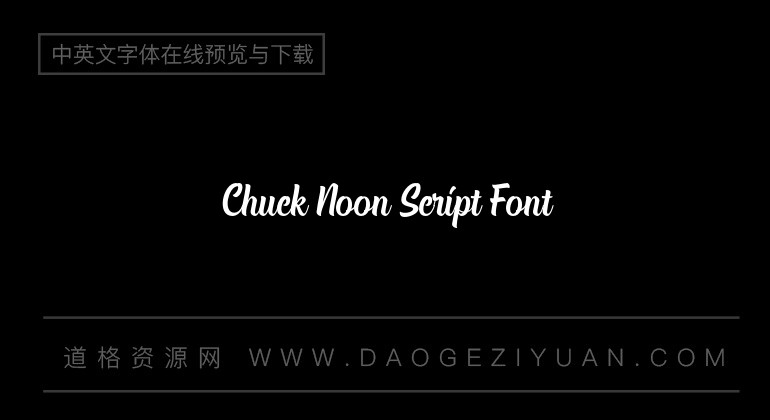
Chuck Noon Script Font 是一种手写字体,具有美丽和独特的外观。该字体设计灵感来自于手写信件,具有流畅的连笔和优美的弧度,使其在印刷品、海报和广告中常常被用于标题和标语。 该字体具有多种字重和斜体版本,可用于许多不同的设计项目。它的字母形状非常自然,适合用于表现个性化和手工风格的品牌、产品或服务。 总之,Chuck Noon Script Font 是一种精美的手写字体,为设计师提供了许多创意和设计选择。内容介绍
Chuck Noon Script Font是一款非常不错的手写艺术字体,具有很好的视觉感,适合于文化类的宣传设计、商业类品牌的广告和产品包装设计以及个性化文字排版等较多场景。